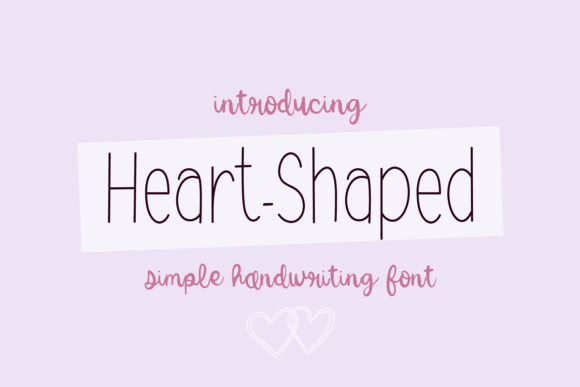
Heart-shaped
適切なデザイン要素を見つけるのは難しい場合がありますが、Heart-shapedは作品を即座に引き立てる優れたコレクションを提供します。
POD(オンデマンド印刷)製品、結婚式の招待状、またはソーシャルメディアのグラフィックを作成している場合でも、Heart-shapedは理想的です。